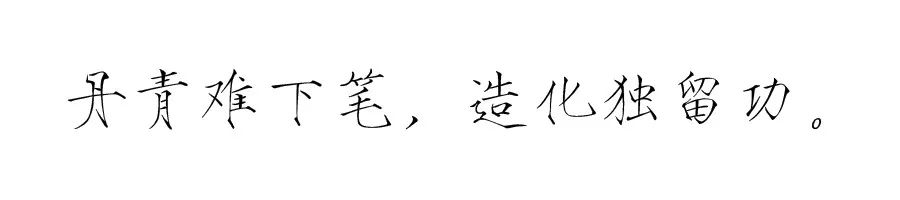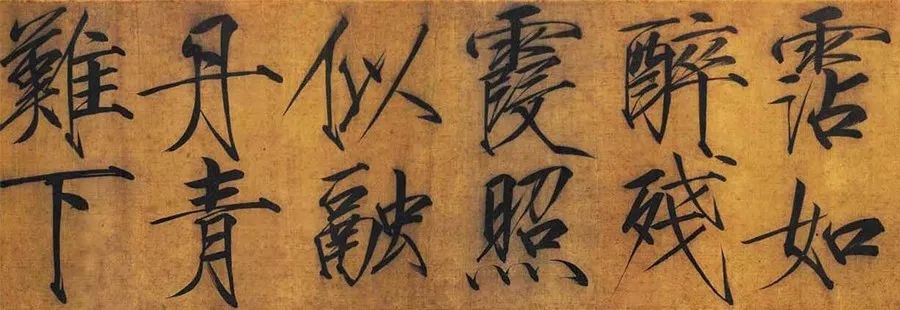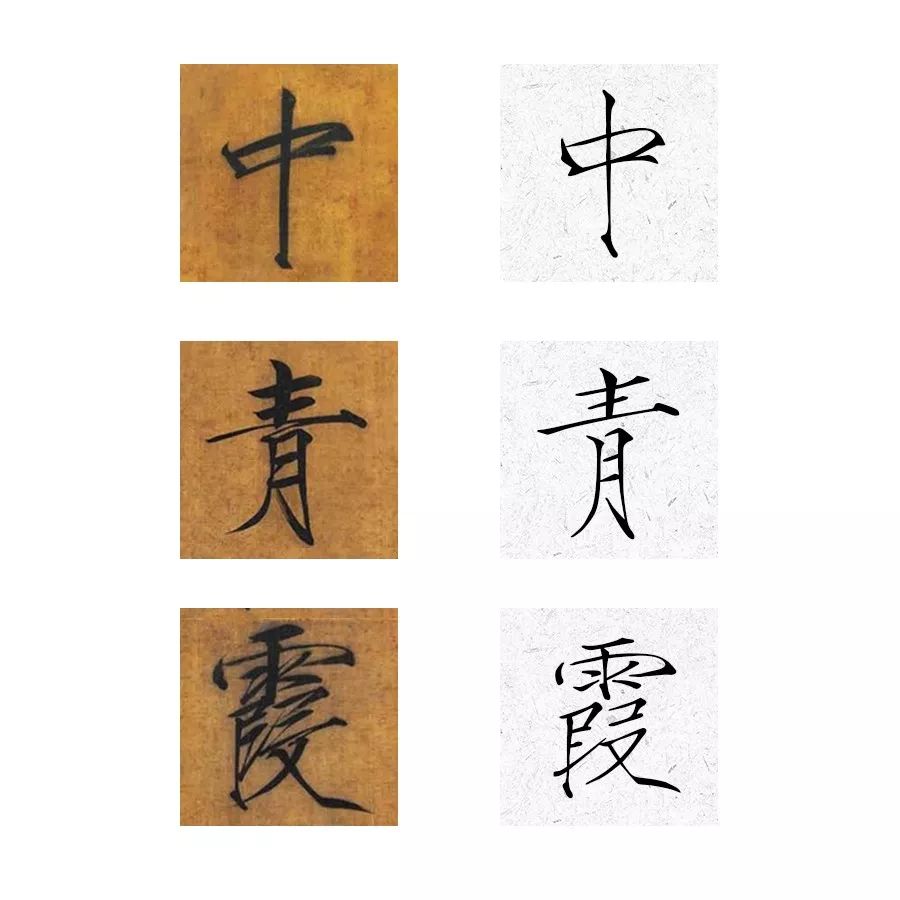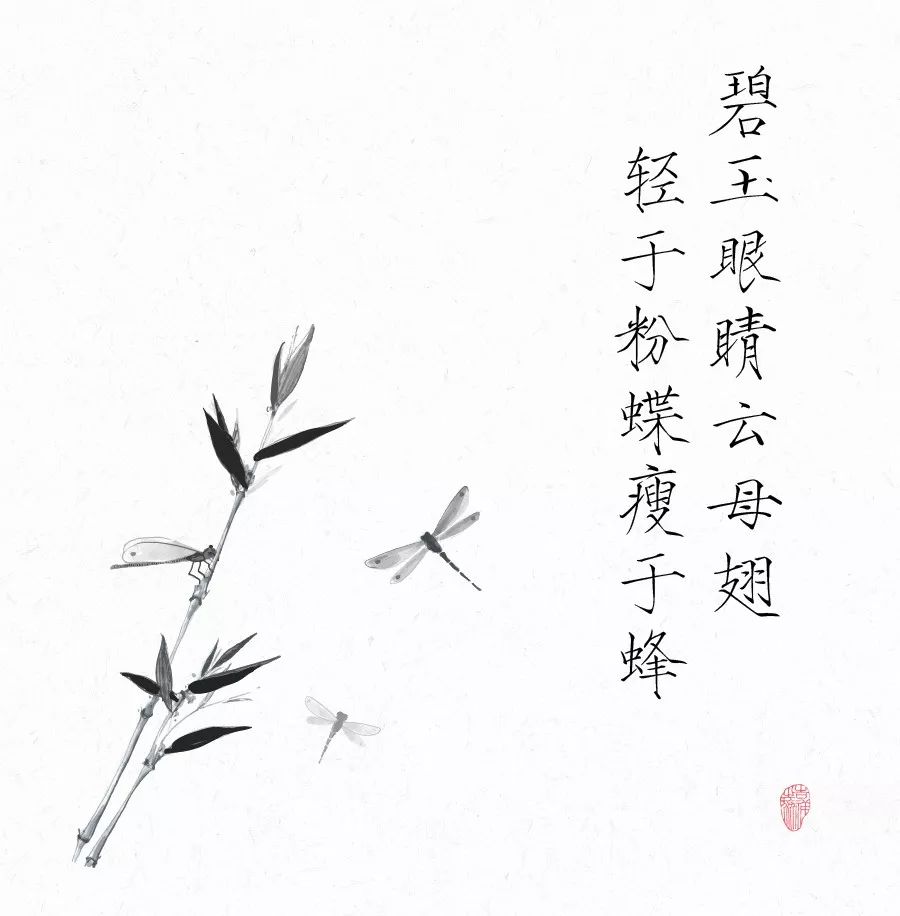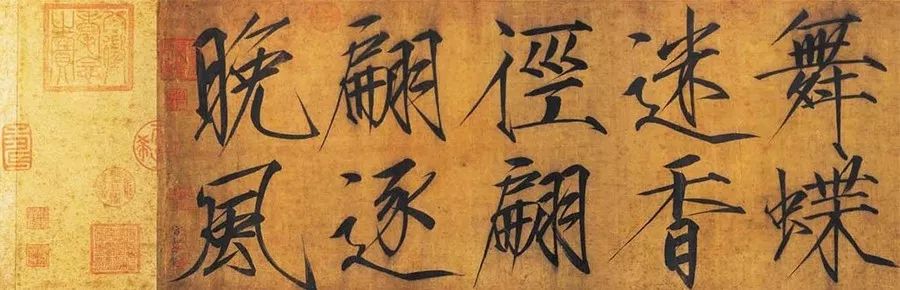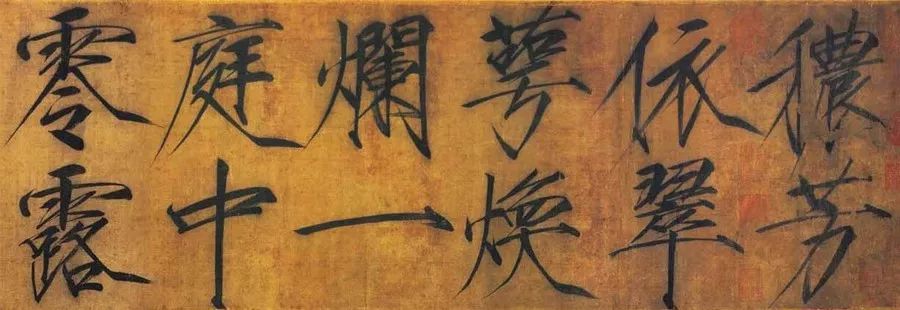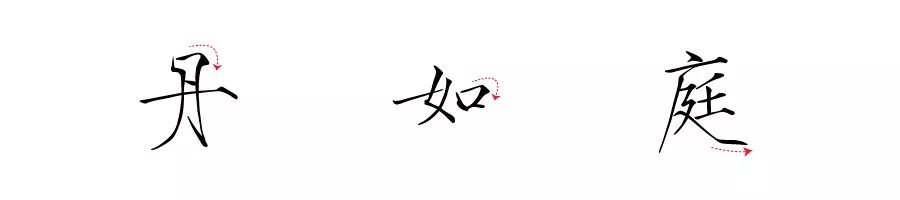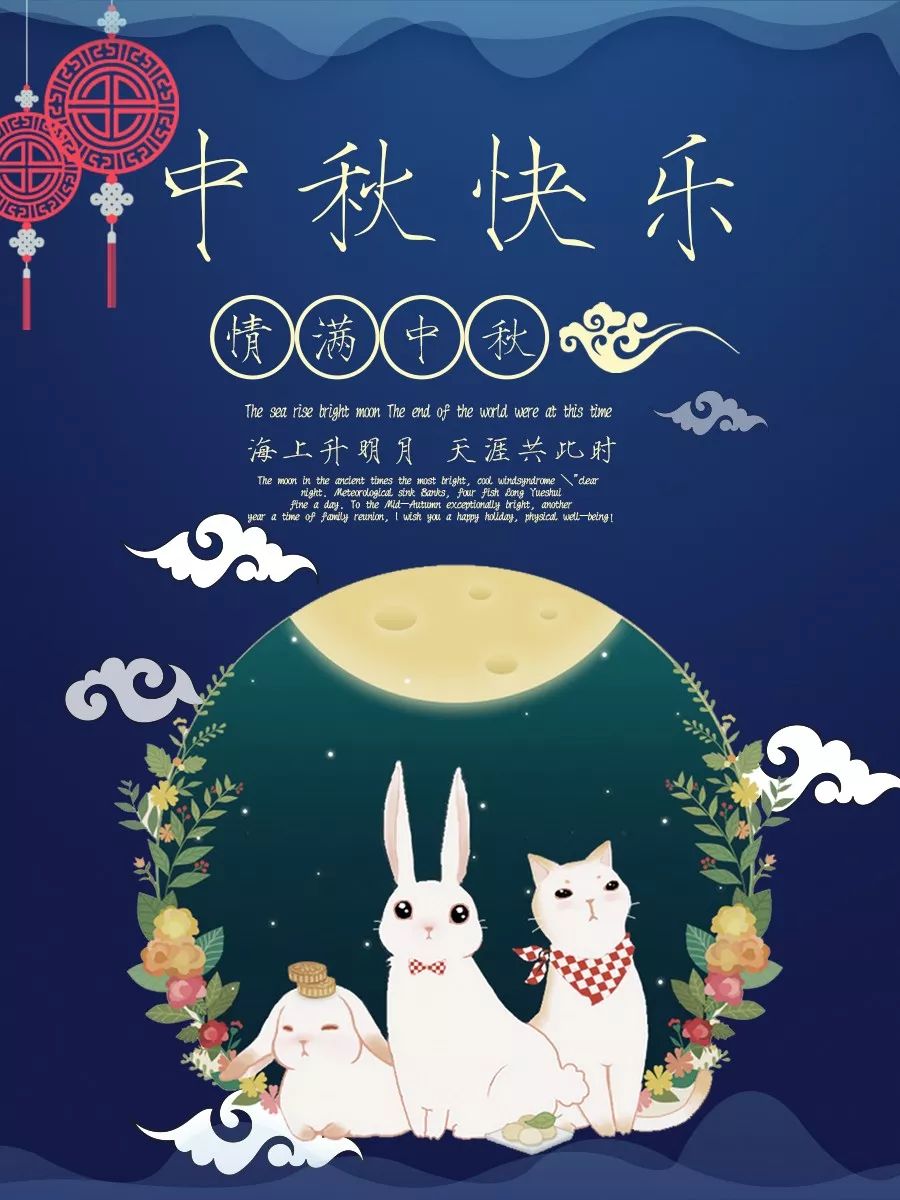
当聊到宋徽宗,除了是宋朝皇帝,还有一个绕不开的事实
宋徽宗—赵佶,北宋斜杠青年:皇帝、书画名家、园林设计师、教主道君皇帝、足球名将(说他踢的不好的都死了)。
一位无心朝政,一心打造文艺娱乐事业的大宋帝国CEO。
虽然身兼数职但在评价“宋老板”时一定要记住一句话“男怕入错行,女怕嫁错郎”。选错专业入错行,这一点宋老板肯定深有同感。宋老板在当时可谓是书画双绝。穿越到当代本应该去中央美院、北大文学系当个教授,却稀里糊涂做了皇帝。让文艺青年来治理国家,注定凶多吉少。
作为一名宋代的斜杆青年,虽然在治理国家上能力不是很优秀。但书画造诣上可谓是掀开了审美艺术的新篇章。而今天就从书法角度聊一聊这位宋代书法名家。
宋老板书法笔画瘦硬,初习黄庭坚,后又学褚遂良和薛稷、薛曜兄弟,并杂糅各家,取众人所长且独出己意,最终创造出别具一格的“瘦金书”体,影响颇大。宋代书法以韵趣见长,宋老板的瘦金书即体现出同类时代审美趣味,又具有强烈的个性色彩所谓“天骨遒美,逸趣霭然。”
这种书体,在前人的书法作品中,未曾出现过。褚遂良的瘦笔,只是小部分相同,大部分则不一样。
褚遂良《倪宽赞》局部图
与唐朝薛曜的字相比,可以说是最接近的。也许宋老板是从薛曜的《石淙诗》变格而来的,但他的创造显然比薛曜成熟得多。
薛曜的《石淙诗》局部图
宋老板留世的作品众多,其中《楷书千字文》是他二十三岁创作此时的瘦金书体已初具规模,而大字《秾芳诗》用笔畅快淋漓,锋芒毕露,富有傲骨之气,如同断金割玉一般,别有一种韵味,堪称瘦金书的杰作。
《秾芳诗》局部图
这种瘦挺爽利、侧锋如兰竹的书体,是需要极高的书法功力和涵养,以及神闲气定的心境来完成的。
后代习其书者甚多,然得其骨髓者寥若晨星,
而这里小编就要说一说出自汉仪字库的——汉仪痩金书
汉仪痩金书运笔灵动快捷,笔迹瘦劲,至瘦而不失其肉,其大字尤可见风姿绰约处。很好了吸收了宋老板《秾芳诗》的精髓。
单字细节对比图
笔画相对瘦硬,笔法外露特点,可明显见到运转提顿等运笔痕迹。
作为少有的痩金书矢量字库产品,虽与宋老板的痩金书相比笔势略显纤弱,但能很好的保留痩金书的“如屈铁断金”韵味以实属不易。